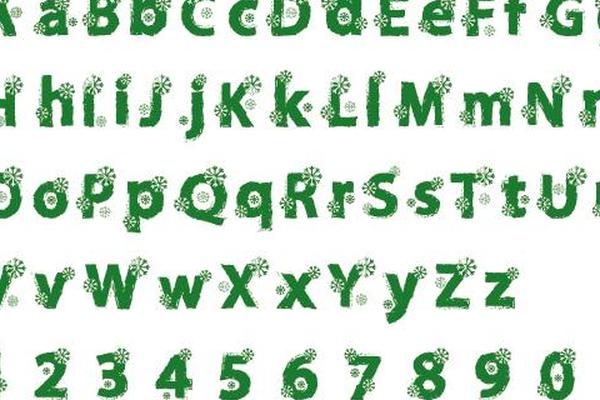
Шрифты — отличный способ улучшить внешний вид любой страницы альбома для вырезок, и рождественские альбомы для вырезок не являются исключением из этого правила. Используйте множество различных рождественских шрифтов, доступных бесплатно, чтобы персонализировать и украсить страницы вашего альбома.
Бесплатный шрифт LoveToKnow
Сайты, предлагающие бесплатные рождественские шрифты
В дополнение к этим двум шрифтам в Интернете есть много других сайтов, на которых можно скачать бесплатные шрифты. Эти буквы можно использовать для заголовков страниц, цитат, текстов рождественских песен или любых других надписей, которые требуются на ваших праздничных страницах. Просмотрите следующие сайты для широкого спектра шрифтов:
Праздничное место
В Holiday Spot есть более 40 различных шрифтов на рождественскую тематику, и все они бесплатны для скачивания и использования. Включены простые текстовые шрифты, графические шрифты, такие как гирлянды огней с буквой внутри каждой, и шрифты в стиле летучей мыши со снежинками и деревьями. Все шрифты загружаются в виде файлов .zip. Нажмите на нужный шрифт; всплывающее окно спросит вас, хотите ли вы сохранить файл. Нажмите «Сохранить», разархивируйте файл и установите шрифт на свой компьютер.
Из шрифта
Da Font содержит более 100 различных рождественских шрифтов, которые можно скачать бесплатно. Сайт позволяет вам вводить текст, чтобы увидеть, как он будет выглядеть в каждом из шрифтов, прежде чем вы загрузите его для удобного просмотра. Шрифты включают полосатый текст леденца, текст с падающим на него снегом и текст, который включает несколько небольших изображений, окружающих каждую букву, таких как украшения и свечи. Нажмите кнопку «скачать», расположенную справа от каждого шрифта. Всплывающее окно предложит вам сохранить файл. Все файлы в формате .zip; разархивируйте их перед установкой.
Шрифты и вещи
В Fonts and Things есть семь различных бесплатных рождественских шрифтов. Во всех шрифтах буквы вырисовываются на фоне изображения, например украшения или рождественской елки. В дополнение к шрифтам на сайте также есть несколько различных рождественских изображений и значков, которые вы можете использовать с текстом, чтобы еще больше украсить страницы вашего альбома. Все шрифты загружаются как «наборы веб-шрифтов». Нажмите на кнопку «Загрузить набор веб-шрифтов»; всплывающее окно предложит вам сохранить файл. Файлы загружаются в формате .zip, и вам нужно будет разархивировать их перед установкой.
Фонт Ривер
Font River предлагает более 90 различных бесплатных рождественских шрифтов, которые вы можете использовать. Доступные дизайны включают шрифты, в которых каждое слово подвешивается к крючку как украшение, шрифты, которые покрывают ваши слова снегом, и шрифты, в которых каждая буква слова представлена как часть ленты на верхней части подарочной коробки. Нажмите на шрифт, чтобы перейти на «тест-драйв» и страницу загрузки. Вы можете скачать шрифт сразу или ввести свой текст для предварительного просмотра шрифта перед загрузкой в разделе «тест-драйв». Чтобы скачать, нажмите кнопку загрузки; всплывающее окно предложит вам сохранить файл. Разархивируйте его перед установкой.
Кислотные шрифты
В Acid Fonts можно скачать более 30 бесплатных рождественских шрифтов. Шрифты включают в себя буквы из бисера, буквы, покрытые снегом, и буквы, окруженные снежинками. Нажмите кнопку «Загрузить», чтобы перейти на страницу, на которой можно ввести текст для предварительного просмотра шрифтом перед загрузкой. Нажмите «загрузить» еще раз на этой странице, чтобы открыть всплывающее окно с предложением сохранить файл в формате .zip. Этот сайт предлагает программу для распаковки файла для вас, если это необходимо.
1001 бесплатных шрифтов
В 1001 Free Fonts есть два разных рождественских шрифта: один с листьями остролиста, а другой с буквами, заключенными в рождественские огни. Оба бесплатны для личного использования. Сайт позволяет предварительно просмотреть шрифт перед загрузкой, нажав кнопку «Предварительный просмотр», расположенную справа от шрифтов. Для загрузки выберите Windows или Mac OS и следуйте инструкциям на своем компьютере.
Выберите шрифт, соответствующий вашему макету
С таким количеством различных бесплатных рождественских шрифтов для альбомов вам не составит труда найти именно тот шрифт, который вам нужен, чтобы украсить и выделить все ваши рождественские воспоминания. Выберите шрифты, которые будут дополнять ваши фотографии и темы для целостного вида.